Bỏ túi ngay bộ font chữ Instagram và những thông tin thú vị về nó. Sáng tạo với phong cách độc đáo!
Bạn đã bao giờ mong muốn tạo ra những bài viết độc đáo và thu hút sự chú ý trên mạng xã hội? Nếu câu trả lời là có, thì font chữ Instagram sẽ là một lựa chọn tuyệt vời dành cho bạn. Với font chữ đặc biệt này, bạn có thể thể hiện phong cách riêng, tạo điểm nhấn và tạo nên trải nghiệm độc nhất vô nhị trên mọi nền tảng. Bài viết này sẽ giúp bạn tìm hiểu về các loại font chữ độc đáo mà Instagram cung cấp và cách bạn có thể tận dụng chúng để tạo nên nét đặc trưng riêng cho các bài đăng của mình.
Mạng xã hội Instagram là gì?
Instagram là một mạng xã hội trực tuyến và ứng dụng chia sẻ hình ảnh và video. Nó được phát triển bởi Kevin Systrom và Mike Krieger và được ra mắt lần đầu vào tháng 10 năm 2010. Instagram ban đầu chỉ cho phép người dùng chia sẻ ảnh và video, nhưng sau đó đã phát triển để bao gồm nhiều tính năng khác như Instagram Story, IGTV và Instagram Reels.
Instagram cho phép người dùng tạo tài khoản cá nhân, chia sẻ các bức ảnh và video với người theo dõi của mình. Người dùng có thể tải lên ảnh và video từ điện thoại di động và chỉnh sửa chúng bằng các bộ lọc và công cụ chỉnh sửa có sẵn trên ứng dụng. Họ cũng có thể thêm chú thích, định vị địa lý và ghim thẻ bạn bè vào bài đăng.
Ngoài việc chia sẻ nội dung, người dùng có thể tương tác với nhau bằng cách thích, bình luận và chia sẻ bài đăng. Instagram cũng cung cấp tính năng phát trực tiếp, cho phép người dùng phát video trực tiếp và tương tác trực tiếp với khán giả của mình.
Instagram đã trở thành một trong những mạng xã hội phổ biến nhất trên thế giới, với hàng tỷ người dùng trên toàn cầu. Nó đã trở thành một nền tảng quảng cáo quan trọng cho các doanh nghiệp và cá nhân, đồng thời cung cấp cơ hội để chia sẻ và khám phá nhiều loại nội dung sáng tạo.
Bộ font chữ Instagram
Bộ font chữ logo Instagram
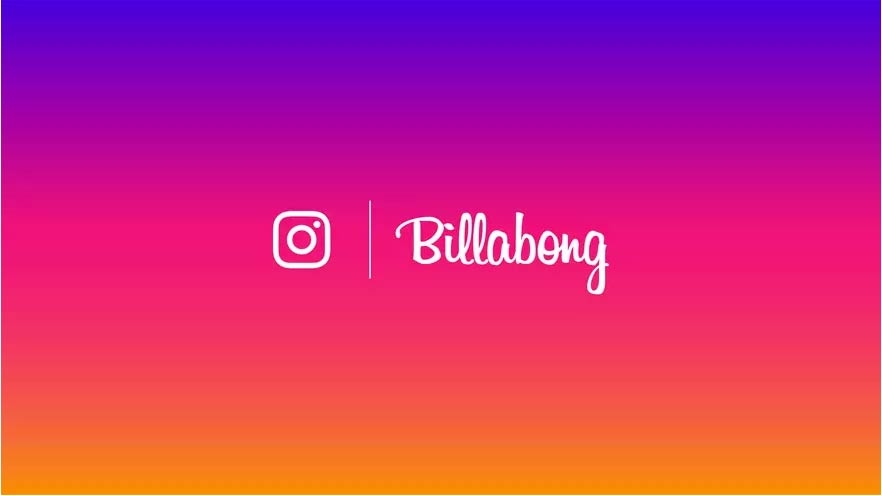
Font chữ chính được sử dụng trong logo Instagram là "Billabong", việc "Billabong" được sử dụng trong logo Instagram đã trở thành biểu tượng của nền tảng này. Với phong cách chữ viết tay, nghệ thuật và mang tính biểu tượng, font chữ Billabong tạo nên tính cá nhân và độc đáo cho thương hiệu Instagram.
Sự mượt mà của nét chữ “Billabong” kết hợp với các yếu tố đặc biệt tạo nên sự cân bằng giữa tính chuyên nghiệp và cá nhân. Nét chữ cong, nhẹ nhàng và nghệ thuật của Billabong tạo ra một hình ảnh thân thiện và hấp dẫn cho Instagram.
Việc sử dụng font chữ Billabong trong logo Instagram không chỉ giúp xác định và tạo nên nhận diện thương hiệu mạnh mẽ, mà còn tạo ra sự gắn kết và nhận diện ngay lập tức từ phía người dùng. Khi nhìn thấy font chữ Billabong, người dùng sẽ liên tưởng ngay đến Instagram và các giá trị mà nền tảng này mang lại.
Bộ font chữ Instagram trong Story
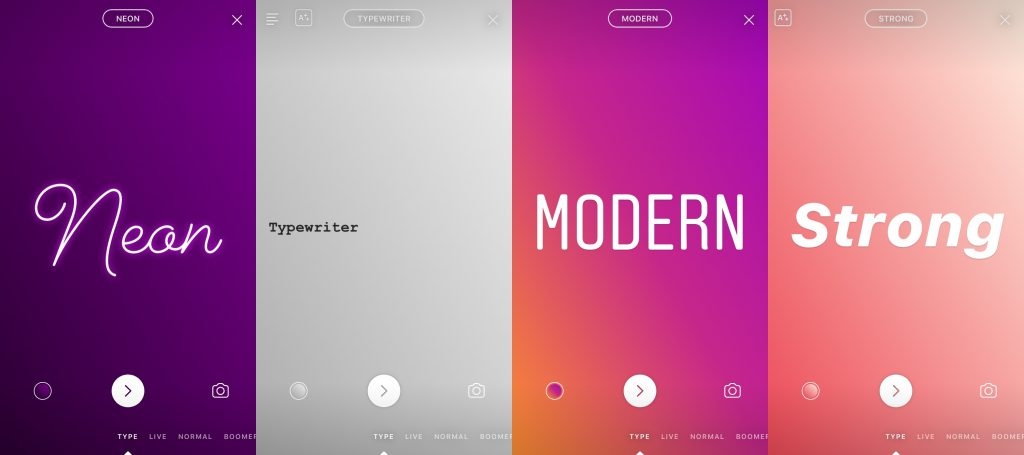
Instagram cung cấp các font chữ tùy chỉnh để người dùng có thể tạo ra trải nghiệm độc đáo trên nền tảng. Bộ font chữ Instagram trong Story cho phép người dùng truy cập và chọn sử dụng nhiều font chữ khác nhau. Dưới đây là các font chữ mặc định được cung cấp:
- Classic: Font chữ có phong cách truyền thống, giữ cho bài viết gần gũi và dễ đọc.
- Modern: Font chữ hiện đại với các đường nét tối giản và sắc sảo, mang đến vẻ ngoài hiện đại và thời thượng.
- Neon: Font chữ có hiệu ứng sáng như đèn neon, tạo điểm nhấn và sự bắt mắt cho bài viết.
- Typewriter: Font chữ đặc trưng của máy đánh chữ, tạo ra vẻ cổ điển và độc đáo.
- Strong: Font chữ đậm, mạnh mẽ và nổi bật, thích hợp cho các thông điệp quan trọng và mang tính chất tuyên bố.
Sự đa dạng và sáng tạo trên Instagram
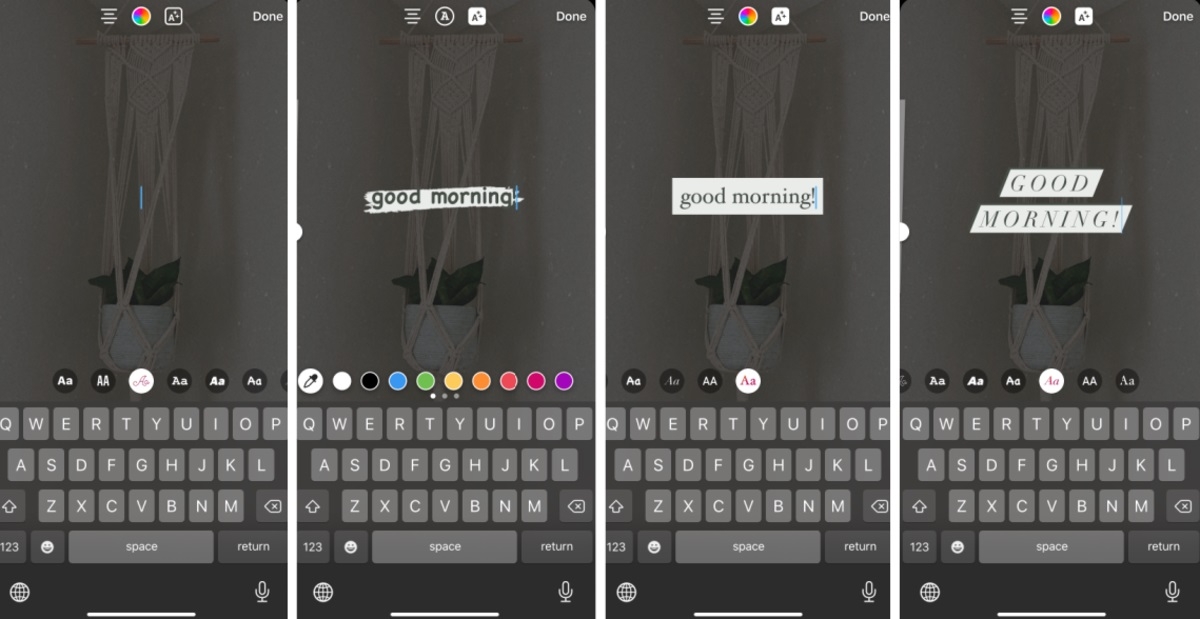
Sự đa dạng và sáng tạo trên Instagram không chỉ xuất hiện trong việc sử dụng các font chữ độc đáo, mà còn trong cách người dùng tạo nội dung và tương tác trên nền tảng này. Instagram cung cấp nhiều tính năng và công cụ cho phép người dùng thể hiện sự sáng tạo của mình.
Với tính năng Story, người dùng có thể tạo những câu chuyện ngắn, chứa hình ảnh, video và văn bản, đồng thời sử dụng các font chữ độc đáo để tạo điểm nhấn và thu hút sự chú ý từ người xem. Các font chữ được sử dụng để thêm phong cách và cá nhân hóa cho câu chuyện của người dùng.
Ngoài ra, việc sử dụng các font chữ độc đáo trong tiêu đề, mô tả và chú thích của bài đăng cũng giúp tạo sự đa dạng và sáng tạo. Người dùng có thể thể hiện tính cá nhân và phong cách riêng của mình thông qua việc chọn font chữ phù hợp với nội dung và tạo điểm nhấn cho bài đăng.
Việc sử dụng các font chữ đa dạng cũng khuyến khích sự tương tác và kết nối giữa người dùng. Khi một người dùng sử dụng một font chữ độc đáo và thu hút sự chú ý, nó có thể tạo ra sự tò mò và khích lệ người khác để tương tác và khám phá nội dung của họ.
Lưu ý nhỏ về font chữ Instagram
Instagram không có một font chữ cụ thể dành riêng cho Insta Story. Khi tạo Story trên Instagram, người dùng có thể lựa chọn từ nhiều font chữ khác nhau có sẵn trong ứng dụng. Các font chữ này bao gồm các font cơ bản như Classic, Modern, Neon và Typewriter, cũng như các font chữ trang trí và mang phong cách riêng như Strong, Italic và Glow. Người dùng cũng có thể truy cập vào các font chữ bổ sung bằng cách sử dụng các ứng dụng từ bên thứ ba hoặc trang web tạo font chữ đặc biệt cho Instagram, sau đó nhập chúng vào Story của mình.